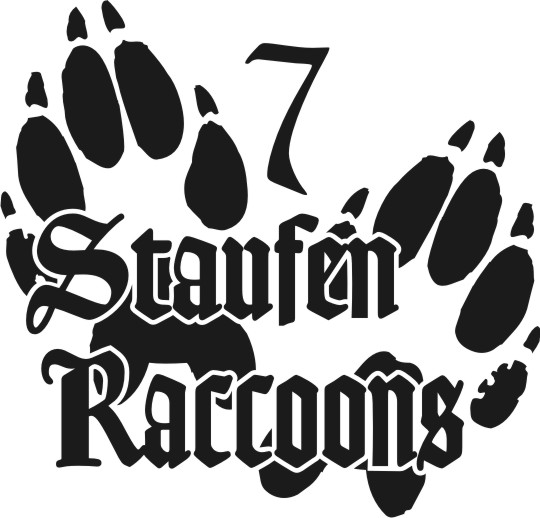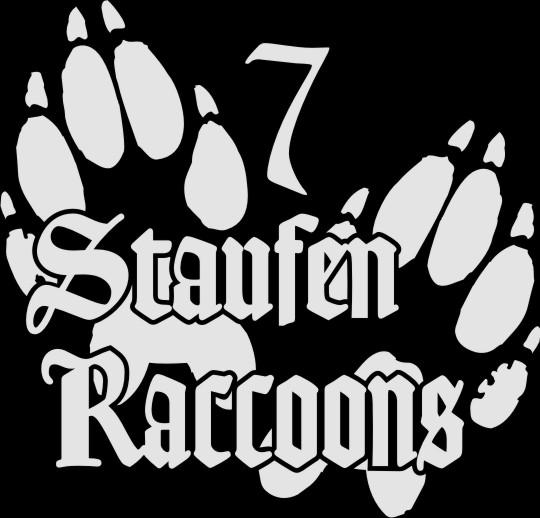
altdeutsche schrift gesucht
vor einigen Jahren wurde angefügtes Logo für unseren Motorradclub von einer kleinen Druckerei erstellt, die es nicht mehr gibt. Was ist das für eine Schrift und kennt vielleicht auch jemand das Bild? Soll eine Tatze eines Waschbärs sein.
die Schrift hat ein bisschen Ähnlichkeit mit der Goudy Text und wirkt wie eine vereinfachte Forma davon ...
Goudy Text
Based on Gutenberg’s 42-line bible.
Designer: Frederic W. Goudy